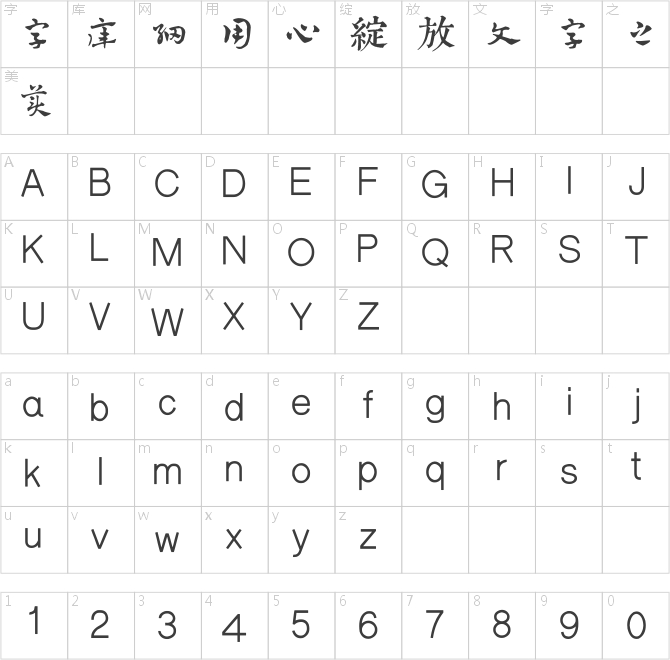
字體名稱: 邯鄲趙雍千字文
作者版權: 韓紹杰
邯鄲趙雍千字文
邯鄲趙雍千字文字體下載邯鄲(元)趙雍千字文
注:本字庫為古籍千字文復刻書法小字庫,字符數量為1000余字,如有特殊需求,可以聯系邯鄲字庫韓紹杰為您訂制,也可以聯系本站客服為您轉答!
趙雍(1289年-1369年),字仲穆,吳興(今浙江湖州)人。元代書畫家。趙孟頫之子。
父趙孟頫為故元翰林學士承旨,贈榮祿大夫,江浙等處中書省平章政事,贈魏國公,詣文敏。母管道升,贈魏國夫人。趙雍以父蔭入仕,官至集賢待制、同知湖州路總管府事。書畫繼承家學,趙孟頫嘗為幻住庵寫金剛經未半,雍足成之,其聯續處人莫能辨。配劉氏,封歸安縣君,三子,鳳,麟,燕;一女淑瑞,適錢塘崔復。
擅山水,尤精人物鞍馬,亦作界畫。書善正、行、草,亦長篆書。精鑒賞。傳世作品有《蘭竹圖》、《溪山漁隱》、《飲中八仙圖》等。
邯鄲趙雍千字文字體邯鄲(元)趙雍千字文字庫是一款讓人賞心悅目、百看不厭的中文字體,適合各類廣告和產品包裝設計應用,字體大小6.37MB,格式為ttf字體,上傳用戶是邯鄲字庫,作者/版權方為韓紹杰